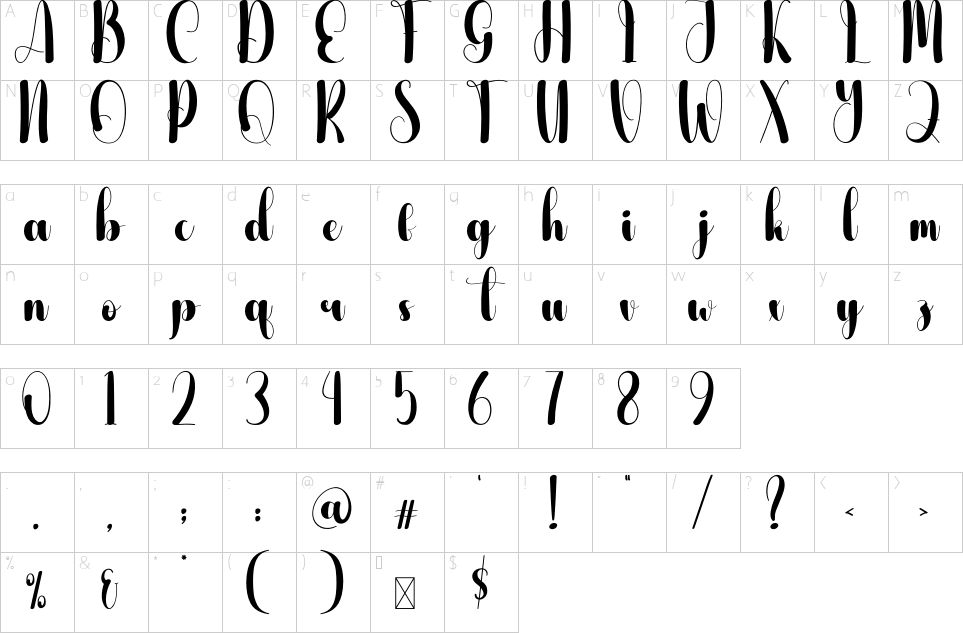
A fonte Greatne é uma opção gratuita que oferece estilo moderno e elegante para a sua próxima projeto gráfico. Desenvolvida por William Jhordy, esta fonte está disponível tanto para Windows quanto para Mac e já foi baixada 505 vezes. Com seu design clean e simples, Greatne é perfeita para textos de texto e headlines em suas páginas web ou impressas. Não deixe de experimentar a versatilidade desta fonte gratuita da nossa gama de 1001 Free Fonts. Tente agora e veja como ela pode adicionar um toque único ao seu trabalho!